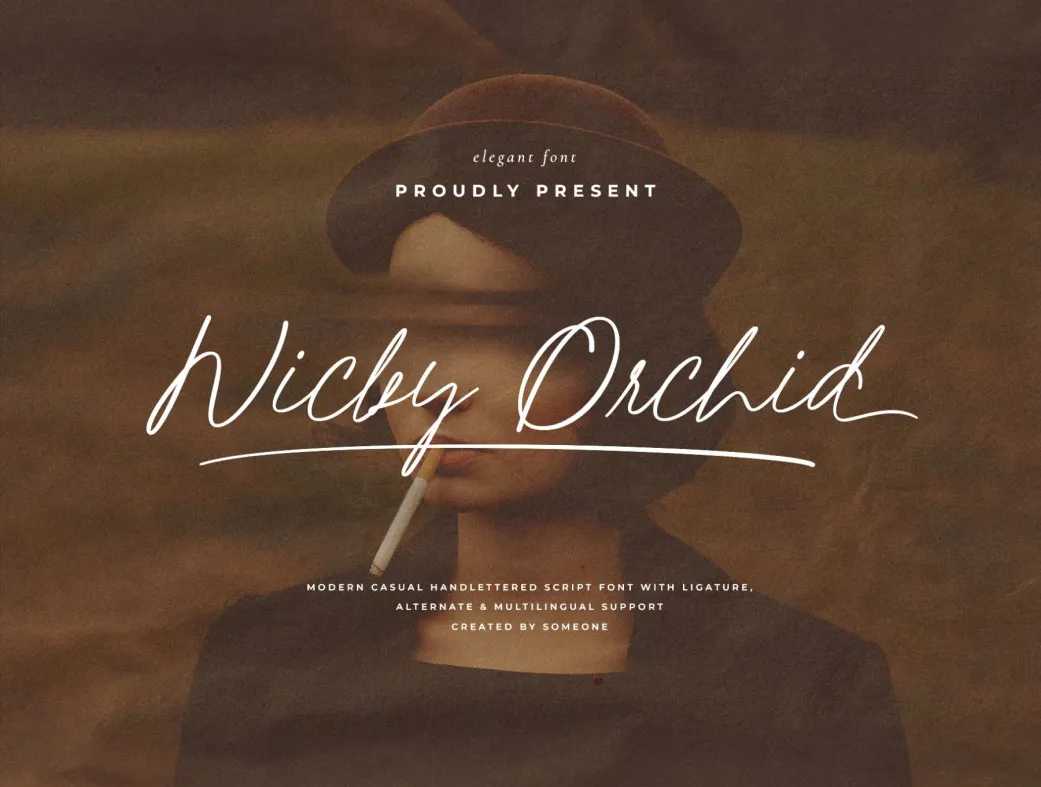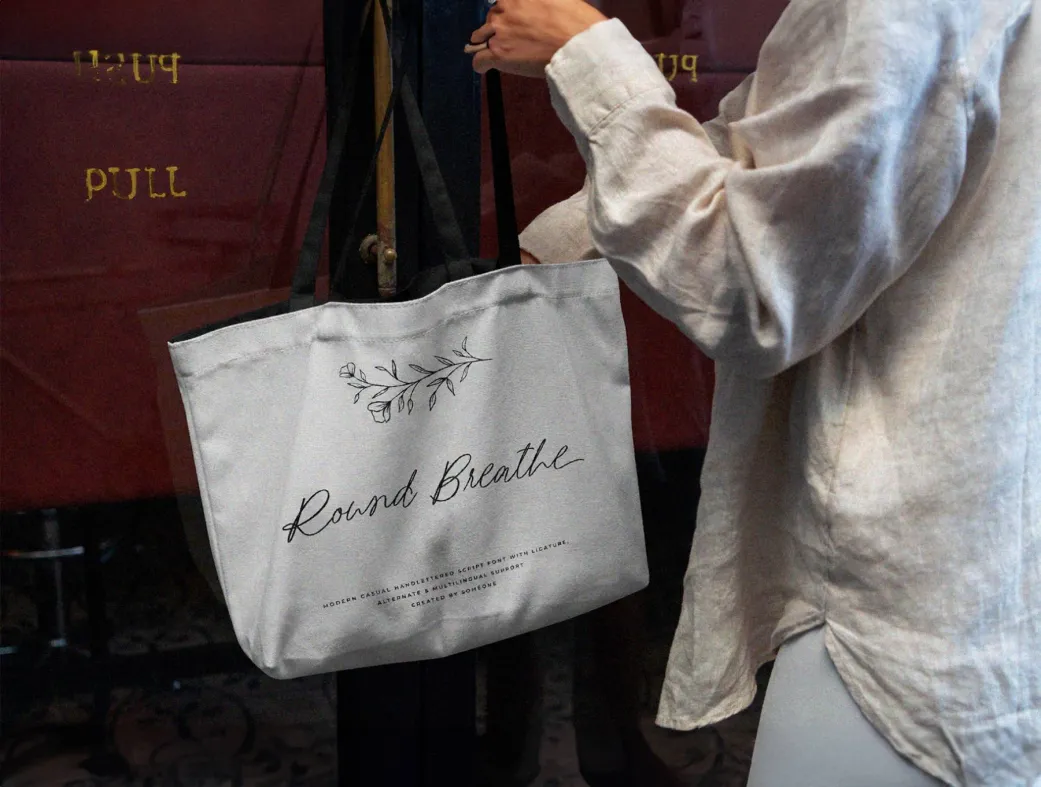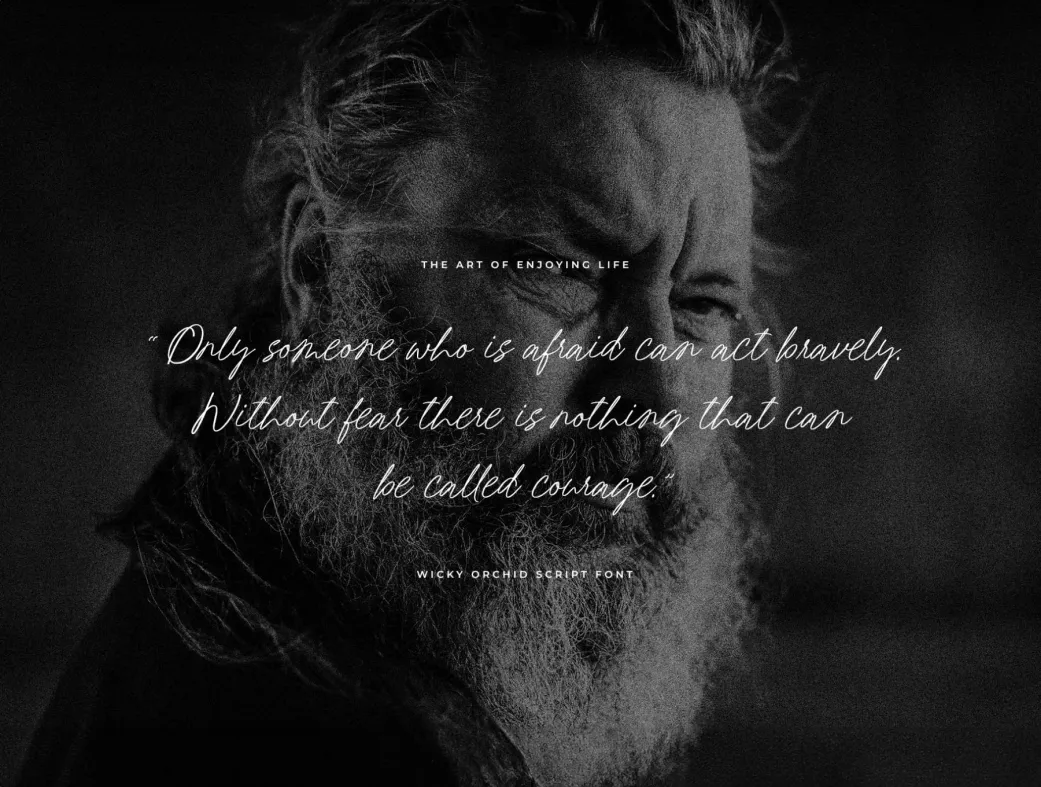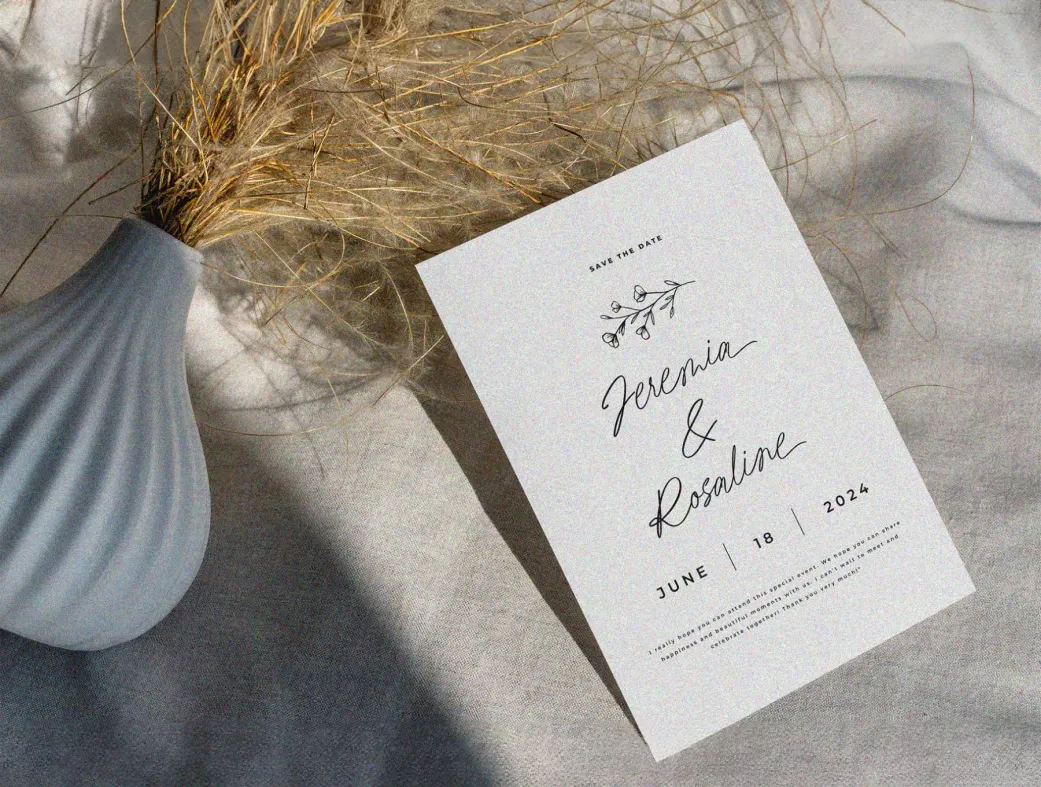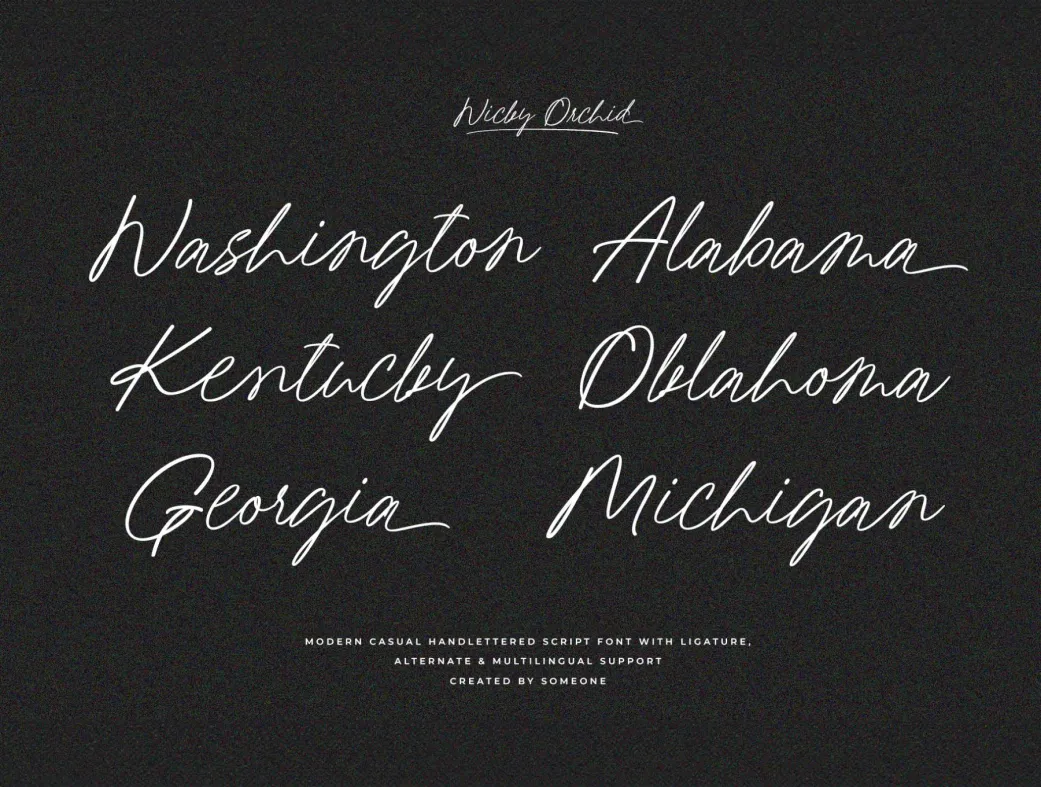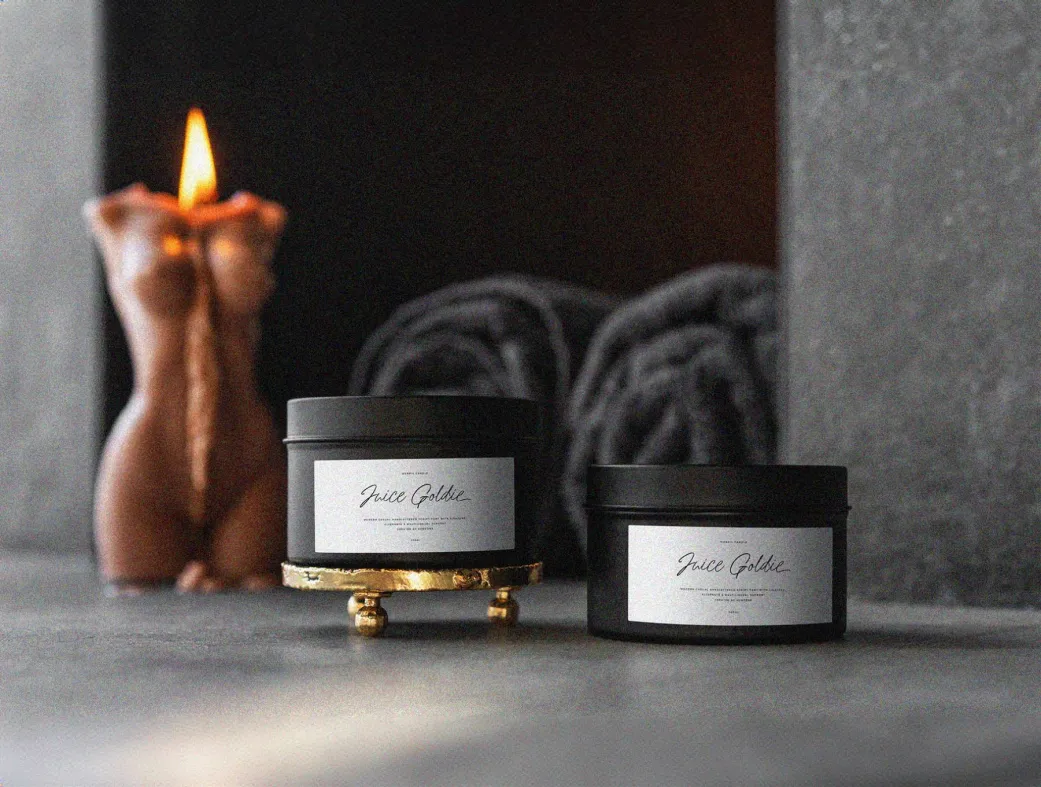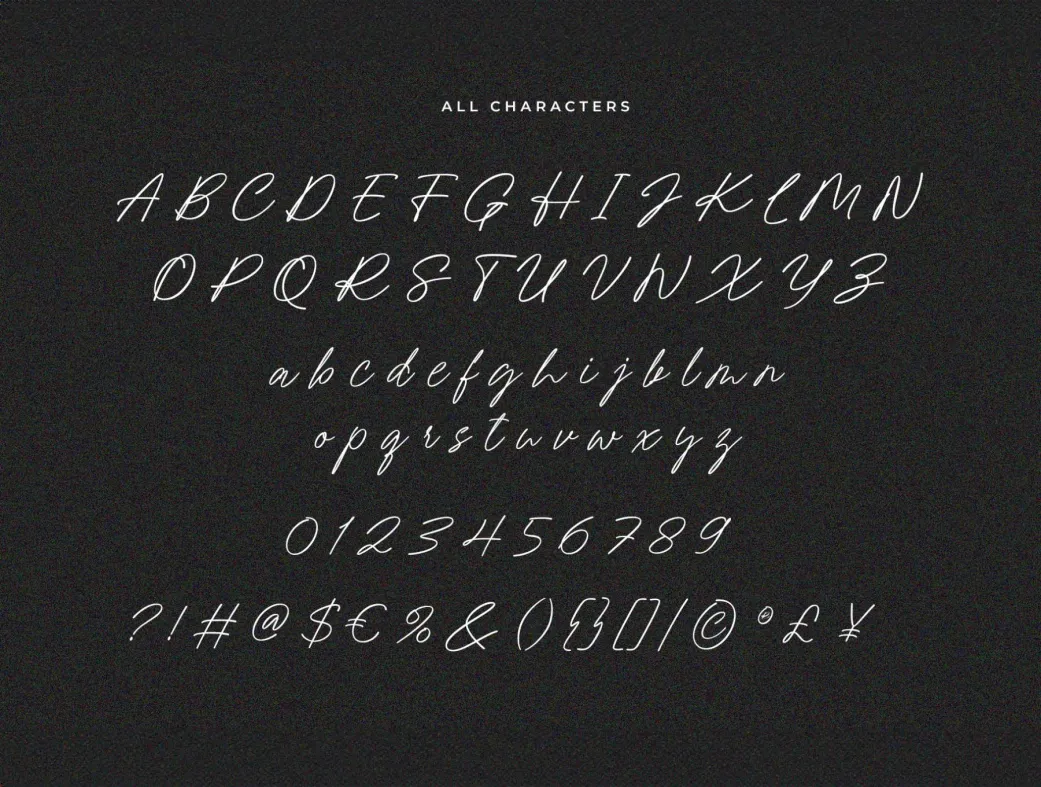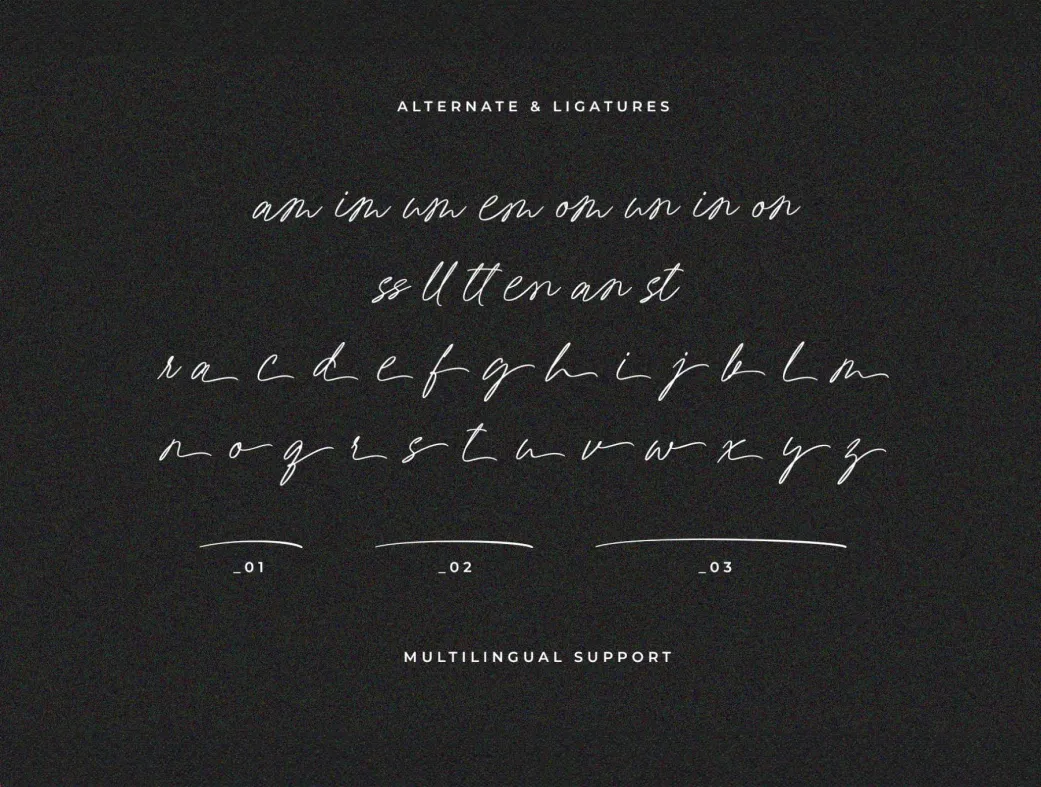
فونت دست‌نویس رایگان ویککی ارکید | Wicky Orchid
آیا به دنبال فونتی منحصر به فرد و دست‌نویس هستید؟ ویککی ارکید، تجربه‌ای خلاقانه و ظریف برای طراحی‌های شماست.
Wicky Orchid - Script Handwriting Font
فونت دست‌نویس رایگان ویککی ارکید | Wicky Orchid | Wicky Orchid Script Font
فونت دست‌نویس ویککی ارکید، شما را به دنیای تایپوگرافی بی‌نظیر و شیک دعوت می‌کند. این فونت تنها یک نوع قلم نیست؛ بلکه بیانگر شخصیت و احساسات خلاقانه شما در پروژه‌های مختلف است. با فرمت‌های OTF و TTF، ویککی ارکید امکان ادغام بی‌نقص در پلتفرم‌ها و برنامه‌های مختلف را فراهم می‌آورد و به طراحی شما جلوه‌ای دست‌ساز و منحصر به فرد می‌بخشد.
فونت ویککی ارکید با ارائه کاراکترهای جایگزین، به شما این امکان را می‌دهد که با سبک‌های مختلف بازی کنید و متن خود را متناسب با حال و هوای محتوای خود تنظیم کنید. این ویژگی به طراحان حرفه‌ای کمک می‌کند تا خلاقیت بیشتری به خرج دهند و به نتایج جذاب‌تری برسند.
علاوه بر این، این فونت از پشتیبانی چند زبانه برخوردار است که به شما اجازه می‌دهد پیام خود را به راحتی در مرزها منتقل کنید. چه در حال طراحی دعوت‌نامه‌ها، مواد برندینگ، یا افزودن زیبایی به وب‌سایت خود باشید، ویککی ارکید ابزاری هنری است که لمسی از ظرافت و جذابیت به نوشته‌های شما می‌افزاید.
این فونت به ویژه برای طراحان گرافیک، وب‌سایت‌ها، و برندها مناسب است. برای کاربران مبتدی، پیشنهاد می‌شود از کاراکترهای پیش‌فرض استفاده کنند، در حالی که کاربران حرفه‌ای می‌توانند با کاراکترهای جایگزین بازی کرده و نتایج منحصر به فردی خلق کنند.
3. آیا این فونت از زبان‌های مختلف پشتیبانی می‌کند؟
بله، ویککی ارکید از چندین زبان پشتیبانی می‌کند و به شما این امکان را می‌دهد که پیام خود را به صورت بین‌المللی منتقل کنید.
5. آیا می‌توانم کاراکترهای جایگزین را در این فونت پیدا کنم؟
بله، ویککی ارکید شامل کاراکترهای جایگزین است که به شما اجازه می‌دهد متن خود را با سبک‌های مختلف سفارشی‌سازی کنید.